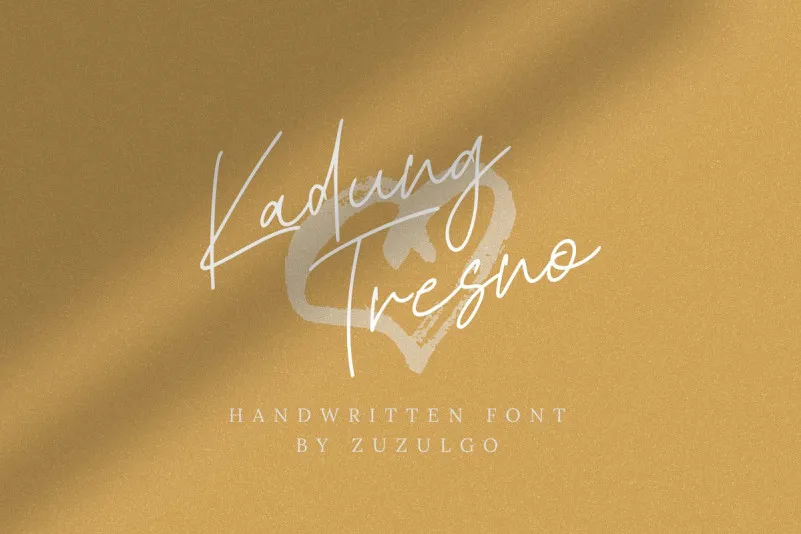
Kadung Tresno Handwritten Font – Download Grátis
Introduzimos a Kadung Tresno Font – uma elegante fonte de script com estilo de escrita original, que parece muito natural e bela. Ela foi criada por zuzulgo e apresentada como um fresco e moderno script de assinatura, projetado para oferecer um visual autêntico e impressionante. A Kadung Tresno Handwritten é perfeita tanto para uso em logotipos quanto em headlines. Ela transmite uma sensação cool e hip, tornando-a ideal para aplicar em invitations, assinaturas, blogs, mídia social, cartões de visita ou marcas. Este design original traz vida à sua marca com um toque autêntico que não se esgota. Tornar seu design único é o nosso objetivo com essa fonte, e a Kadung Tresno Handwritten atende perfeitamente às suas necessidades ao oferecer um estilo único para seus projetos. Não importa o formato do seu trabalho, seja digital ou impresso, esta fonte trará vida e personalidade aos seus designes.